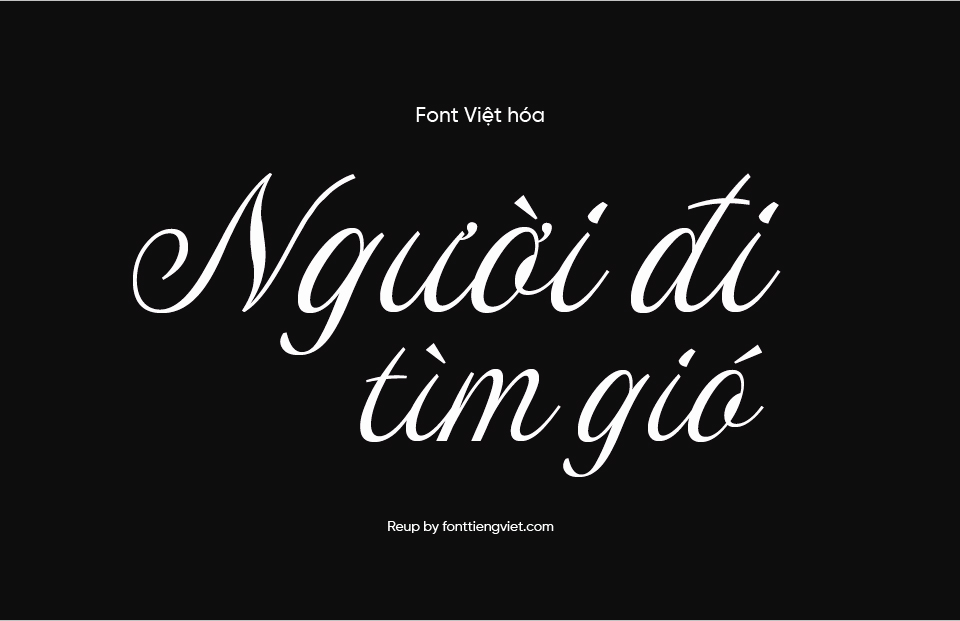
Trong môi trường học thuật, việc trình bày tài liệu rõ ràng, chuyên nghiệp là yếu tố then chốt. Sự lựa chọn Font Chữ không chỉ ảnh hưởng đến tính thẩm mỹ mà còn tác động trực tiếp đến khả năng đọc hiểu và sự nghiêm túc của bài giảng hay đề thi. Gần đây, cộng đồng thiết kế và giáo dục đang xôn xao về bộ Font Việt hóa MTD Genia – một lựa chọn hoàn hảo cho việc soạn thảo các tài liệu học tập, luận văn và đặc biệt là các đề thi tốt nghiệp quan trọng. Bài viết này sẽ đi sâu vào những ưu điểm nổi bật và hướng dẫn bạn cách tải về, sử dụng bộ font chất lượng cao này để tối ưu hóa tài liệu học đường của bạn.
Font Việt hóa MTD Genia: Sự Lựa Chọn Hàng Đầu Cho Giáo Dục
Đối với các trường học, giáo viên và học sinh trung học phổ thông, việc tìm kiếm một font chữ vừa đẹp, vừa dễ đọc, lại hỗ trợ tiếng Việt đầy đủ luôn là một thử thách. Font Việt hóa MTD Genia đã ra đời để giải quyết triệt để vấn đề này. Đây là phiên bản được tối ưu hóa từ font gốc Genia nổi tiếng, bổ sung đầy đủ các ký tự đặc biệt, dấu câu, và đặc biệt là hệ thống dấu thanh tiếng Việt chính xác, giúp người dùng yên tâm khi sử dụng trong mọi văn bản chính thức.
Bộ font này được đánh giá cao vì tính chuyên nghiệp và tính ứng dụng rộng rãi. Không chỉ giới hạn trong việc soạn thảo giáo trình hay tài liệu ôn thi, MTD Genia còn được nhiều người dùng lựa chọn để thiết kế bìa sách, trình bày báo cáo khoa học, và thậm chí là xây dựng thương hiệu cá nhân của các giảng viên. Khả năng hiển thị trên nhiều nền tảng và thiết bị khác nhau, từ máy tính cá nhân đến máy in tài liệu, cũng là một điểm cộng lớn khiến MTD Genia trở thành font chữ phổ biến trong giới học đường.
Đặc Điểm Vượt Trội Của Font MTD Genia Phiên Bản Việt Hóa
Điều gì làm nên sự khác biệt của MTD Genia so với các font chữ miễn phí khác? Đầu tiên phải kể đến độ rõ nét tuyệt vời. Font được thiết kế với các nét chữ cân đối, khoảng cách chữ (kerning) và khoảng cách dòng (leading) được tính toán kỹ lưỡng, đảm bảo văn bản không bị rối mắt ngay cả khi in ấn với cỡ chữ nhỏ. Điều này cực kỳ quan trọng đối với các tài liệu học tập dày đặc chữ như sách giáo khoa hay các đề thi trắc nghiệm.
Thứ hai là sự đa dạng về phong cách. MTD Genia thường đi kèm với nhiều biến thể (styles) như Regular, Italic, Bold, và Bold Italic, cho phép người dùng linh hoạt tạo điểm nhấn cho các tiêu đề, đoạn văn quan trọng, hoặc các công thức toán học phức tạp. Việc sử dụng các biến thể này một cách hợp lý sẽ giúp tăng tính chuyên nghiệp và dễ theo dõi cho người đọc. Phiên bản Việt hóa chất lượng cao đảm bảo rằng các dấu tiếng Việt không bị lỗi font hay che khuất các ký tự gốc, giữ nguyên vẻ đẹp thiết kế ban đầu.
Ứng Dụng Thiết Thực Của MTD Genia Trong Giai Đoạn Ôn Thi
Trong giai đoạn nước rút chuẩn bị cho các kỳ thi quan trọng, đặc biệt là kỳ thi Tốt nghiệp Trung học Phổ thông, giáo viên cần cung cấp tài liệu ôn thi chất lượng cao và dễ đọc. Font Việt hóa MTD Genia giúp các tài liệu này đạt được tiêu chuẩn cao về mặt hình thức. Khả năng tạo ra các bảng biểu, công thức và đoạn văn bản rõ ràng giúp học sinh tập trung vào nội dung mà không bị phân tâm bởi lỗi hiển thị hoặc font chữ kém chất lượng. Đây là một công cụ hỗ trợ đắc lực trong việc tối ưu hóa hiệu quả học tập.
Ngoài ra, MTD Genia còn rất phù hợp cho việc trình bày các bài luận văn, dự án cuối cấp. Tính chuyên nghiệp và nghiêm túc của font giúp nâng cao giá trị hình thức cho bài viết, tạo ấn tượng tốt với hội đồng chấm thi. Sinh viên đại học cũng thường xuyên tìm kiếm các font chữ kiểu này để sử dụng trong đồ án và báo cáo khoa học, cho thấy tính ứng dụng lâu dài của MTD Genia vượt ra khỏi phạm vi trường học phổ thông.
Tóm lại, Font Việt hóa MTD Genia là một tài sản quý giá cho bất kỳ ai làm việc trong lĩnh vực giáo dục hay thiết kế tài liệu chuyên nghiệp. Với khả năng hiển thị tiếng Việt hoàn hảo, tính thẩm mỹ cao và độ rõ nét tuyệt vời, nó xứng đáng trở thành font chữ tiêu chuẩn mới cho các trường học và trung tâm ôn luyện. Đừng ngần ngại khám phá và áp dụng bộ Font Chữ đặc biệt này để nâng cao chất lượng tài liệu của bạn, tạo ra những ấn phẩm học thuật chất lượng, phục vụ tốt nhất cho mục tiêu giáo dục và chuẩn bị cho các kỳ thi tốt nghiệp quan trọng sắp tới.